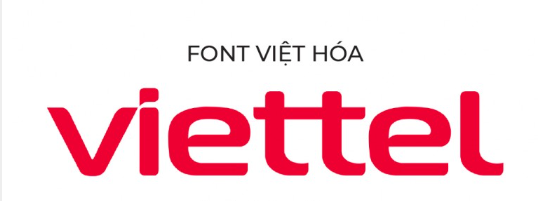
Font Viettel là font chữ thuộc bộ font chữ việt hóa. Font Viettel là một loại font chữ đặc trưng được thiết kế riêng cho các ấn phẩm và tài liệu của Tập đoàn Viễn thông Quân đội Viettel. Với thiết kế hiện đại, dễ đọc và phù hợp với thương hiệu, font Viettel giúp tạo nên sự đồng nhất và chuyên nghiệp trong các sản phẩm truyền thông của tập đoàn. Đối với những ai làm việc trong lĩnh vực thiết kế đồ họa hoặc soạn thảo văn bản cho Viettel, việc sử dụng đúng font chữ này không chỉ góp phần duy trì tính nhận diện thương hiệu mà còn nâng cao chất lượng thẩm mỹ của sản phẩm.